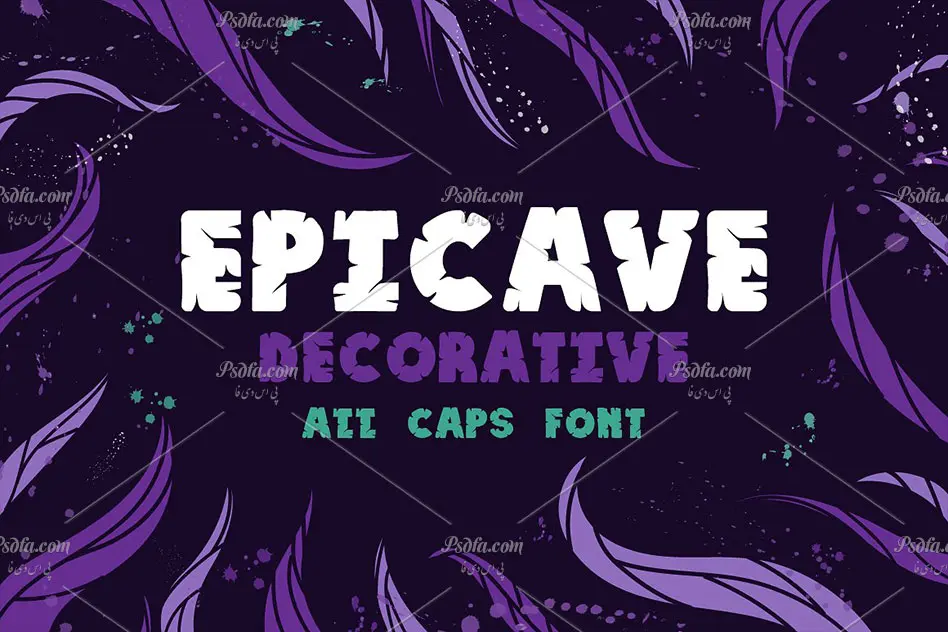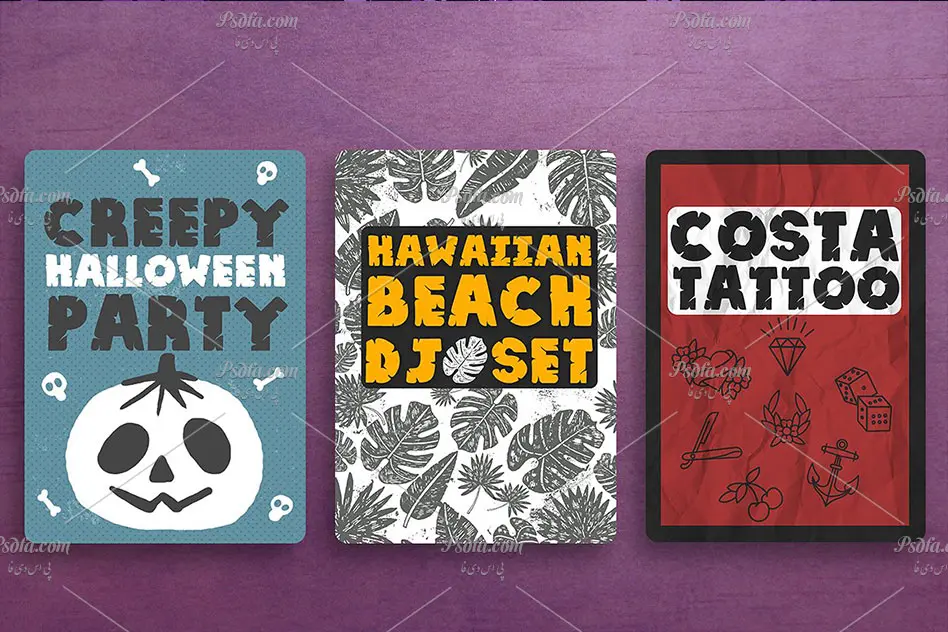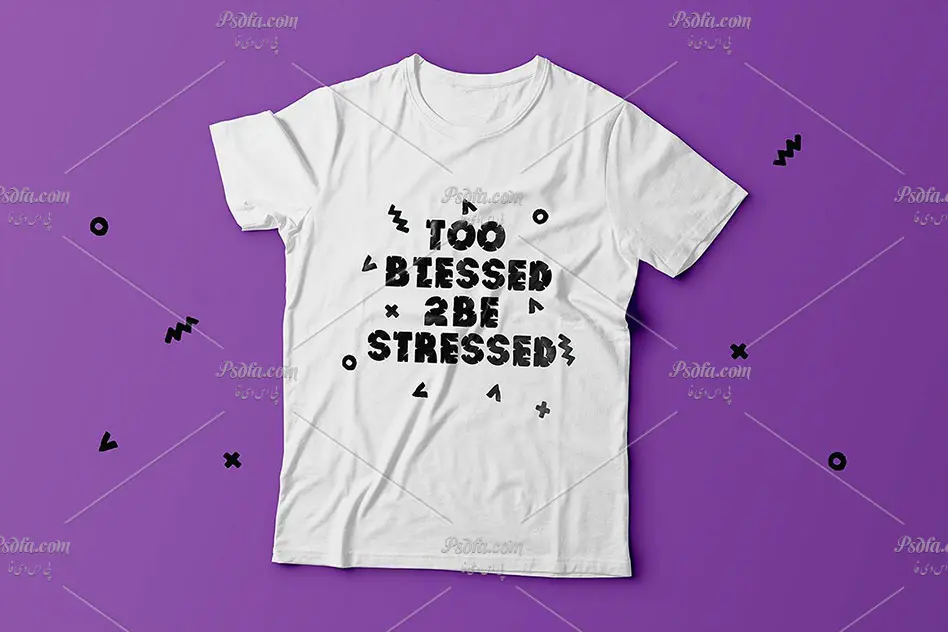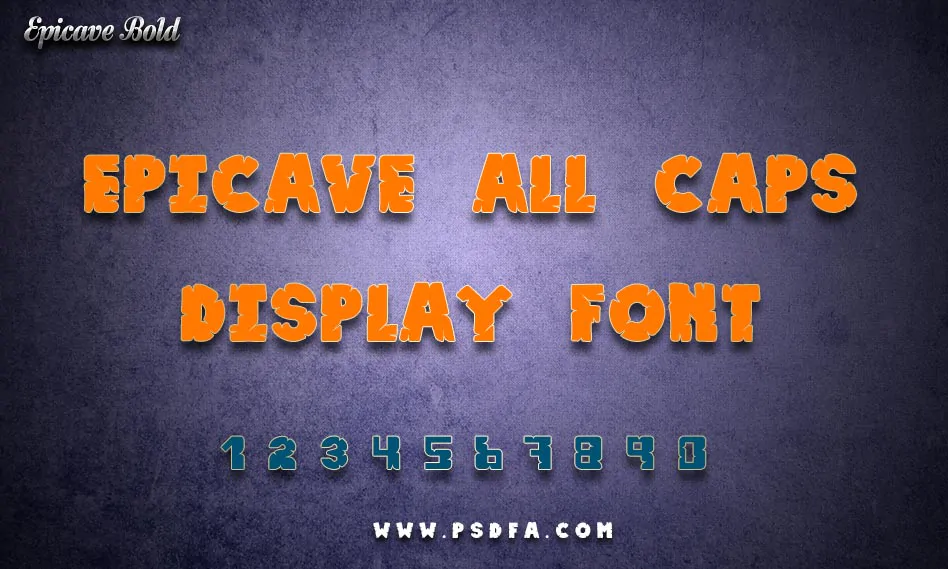
در این مطلب شاهد فونت انگلیسی Epicave Bold مناسب جهت استفاده در طراحی و گرافیک می باشید. این فونت فوق العاده زیبا که از کیفیت بالایی برخوردار است با سه فرمت otf , ttf و woff در سایت قرار داده شده است که پس از نصب آن در سیستم قادر خواهید بود از آن در تمام نرم افزارهای گرافیکی و ویرایشگر متن از جمله نرم افزار فتوشاپ ، مجموعه نرم افزار آفیس و … استفاده کنید. از این فونت زیبا می توان جهت اهداف و مقاصد گوناگون از جمله طراحی انواع پوستر ، طراحی و چاپ بر روی پارچه و لباس ، طراحی بر روی بسته بندی محصولات و … استفاده کرد. اگر از طراحان و گرافیستان این گونه طرح ها هستید به شما پیشنهاد می کنیم این فونت زیبا را از دست ندهید. پیش نمایش این فونت انگلیسی را می توانید در گالری تصاویر زیر یا تصویر فوق مشاهده فرمائید.